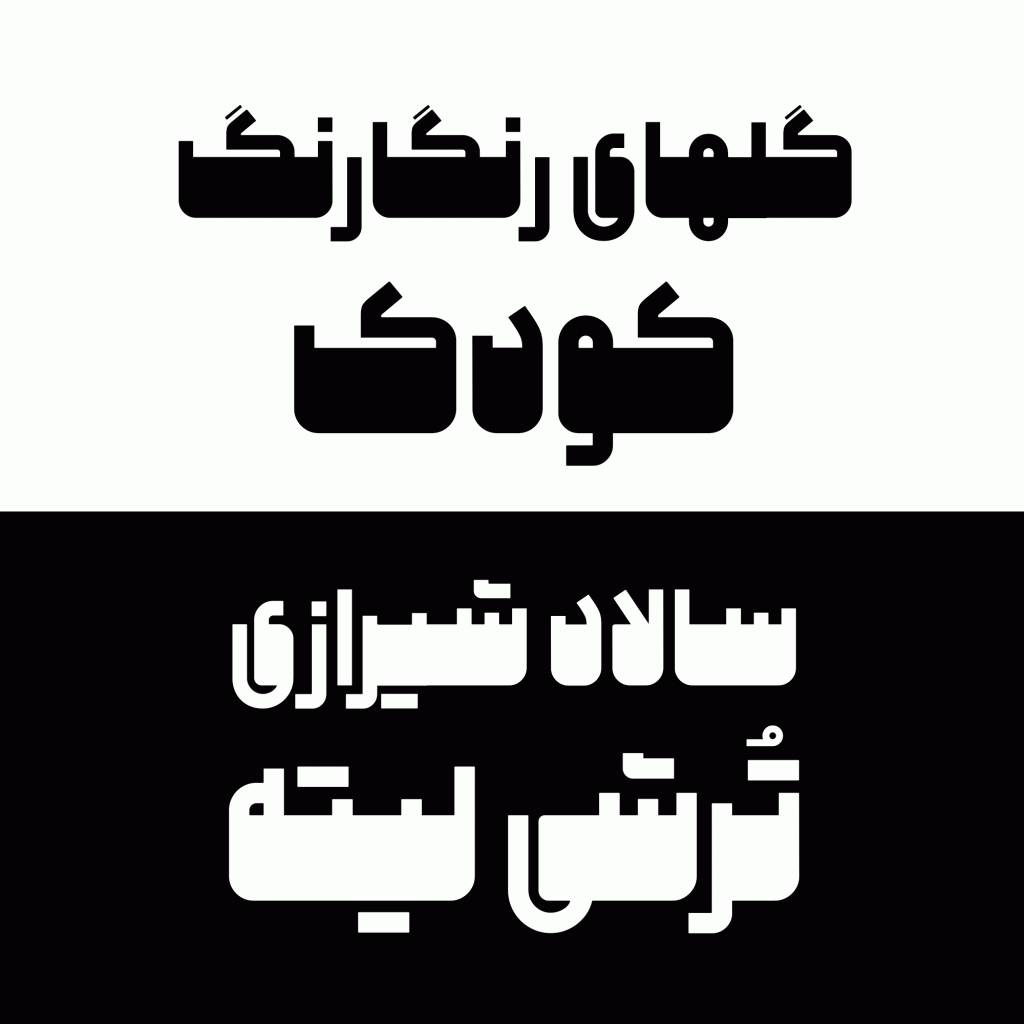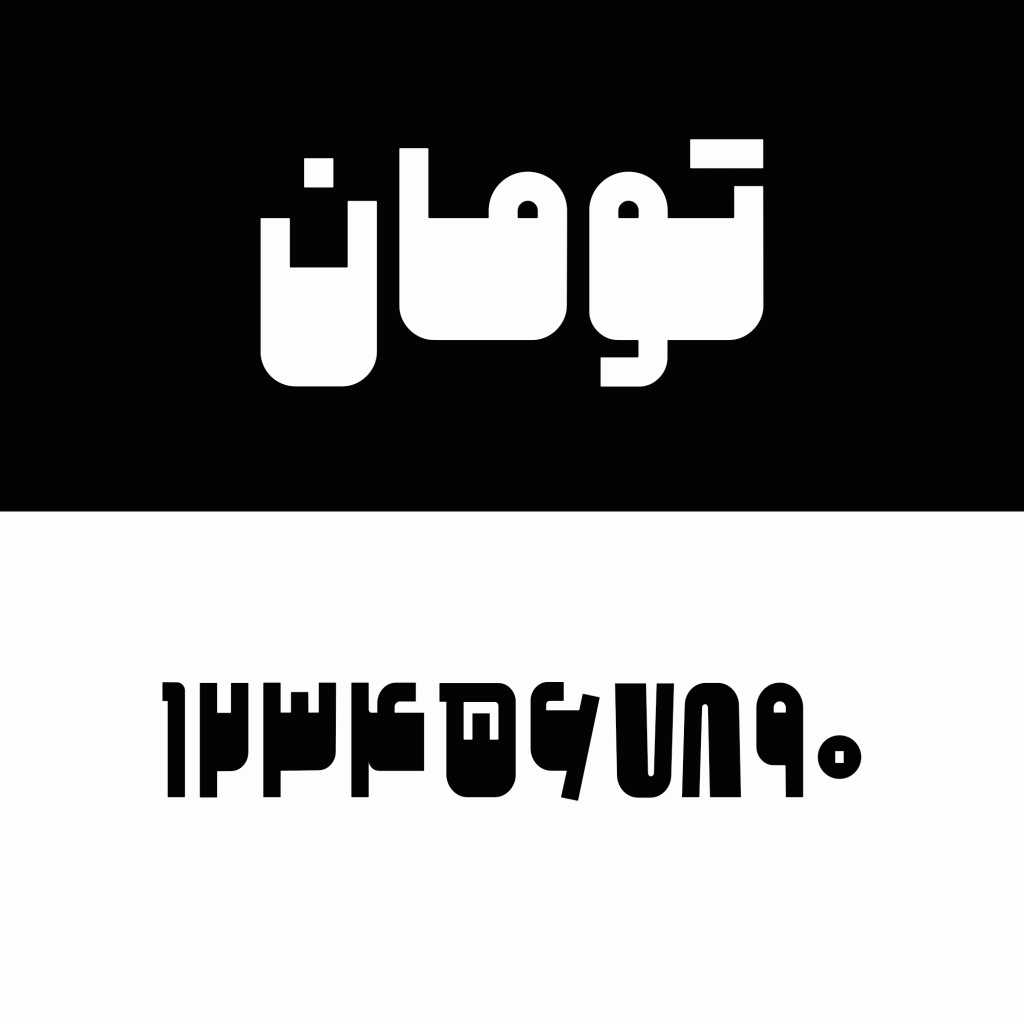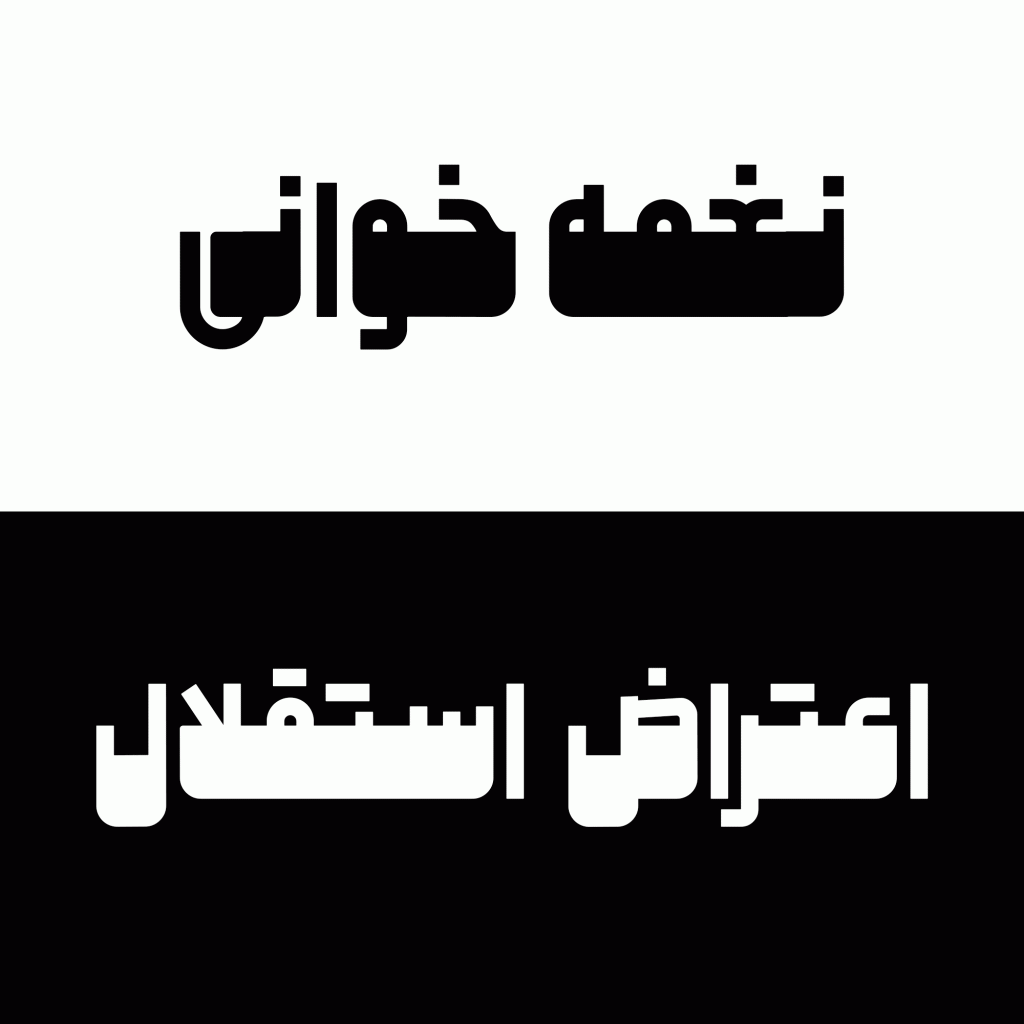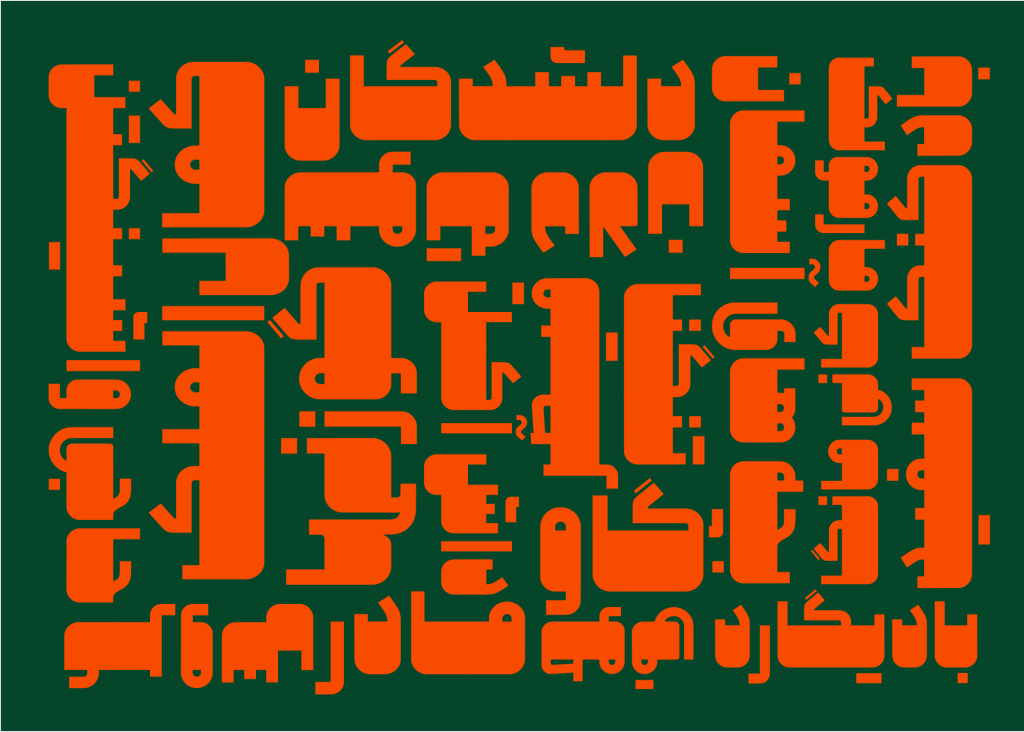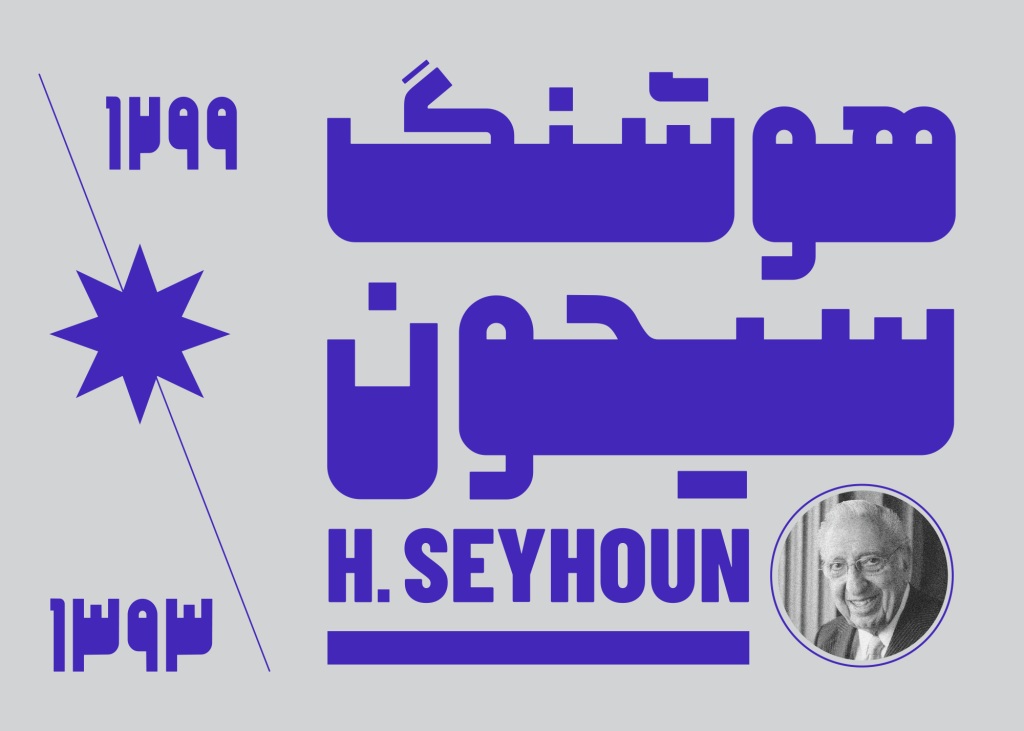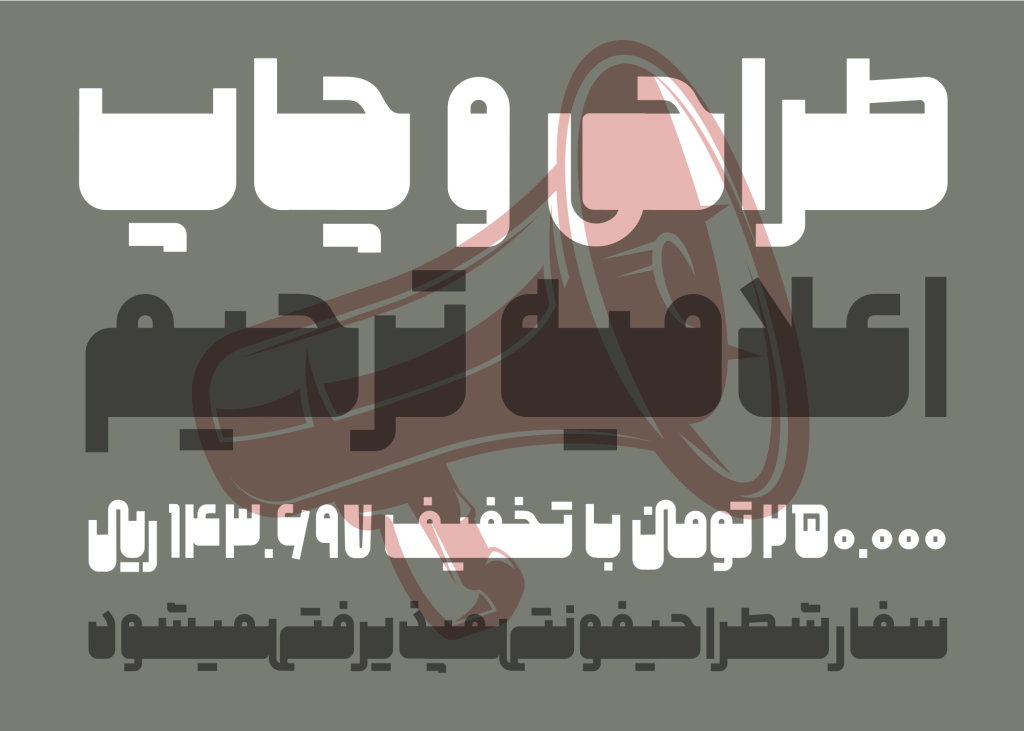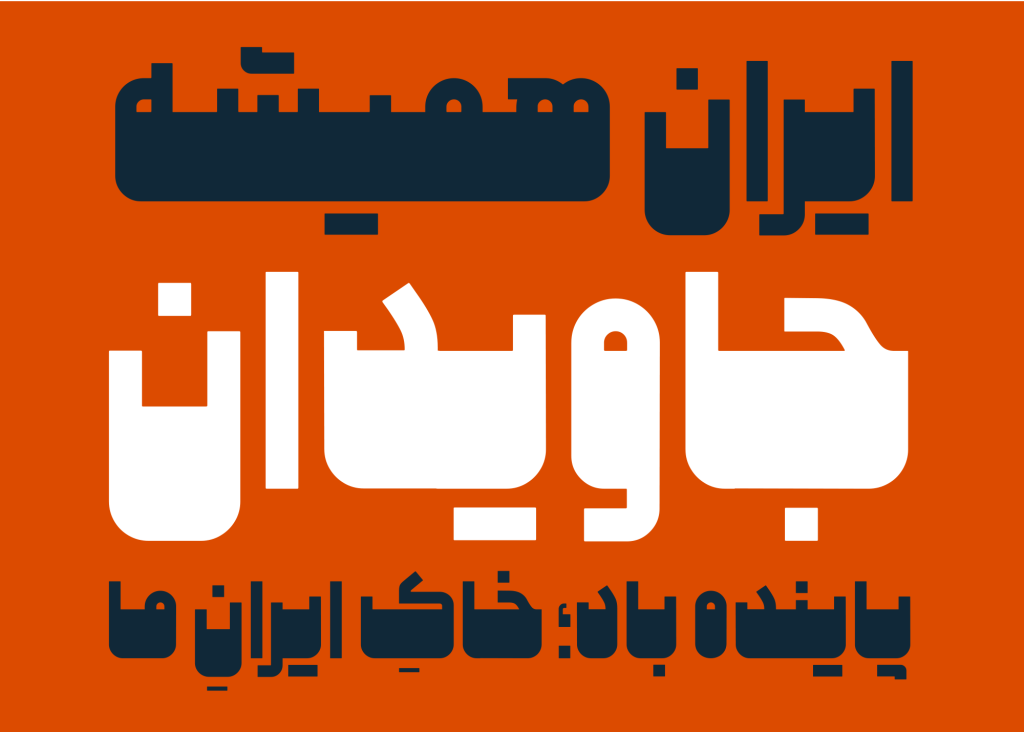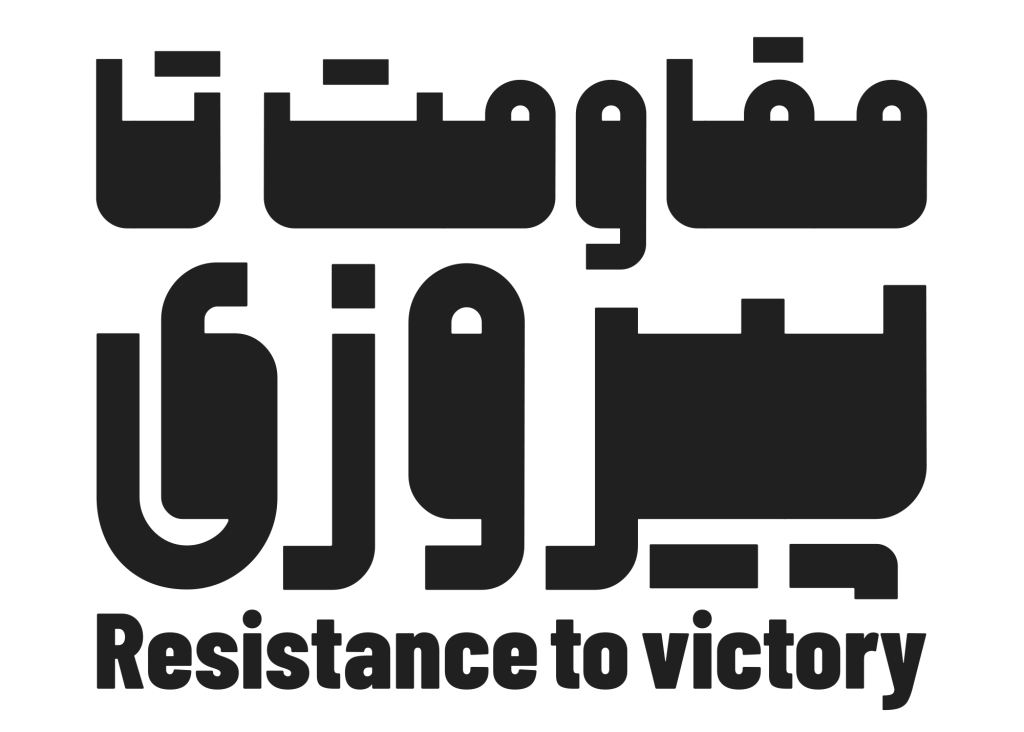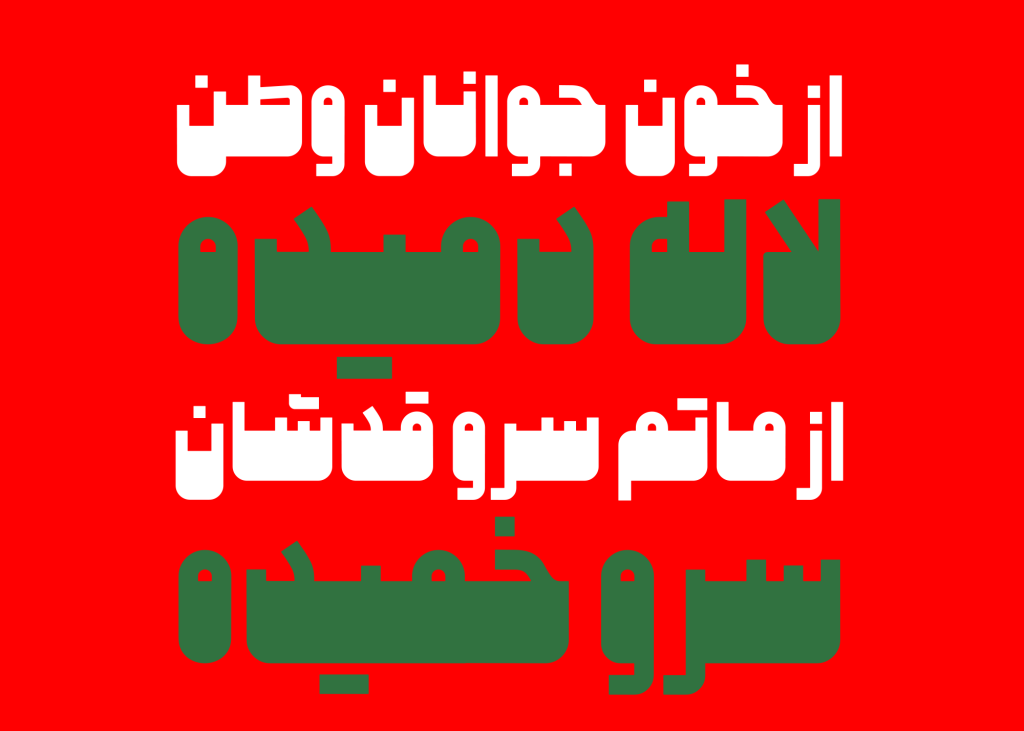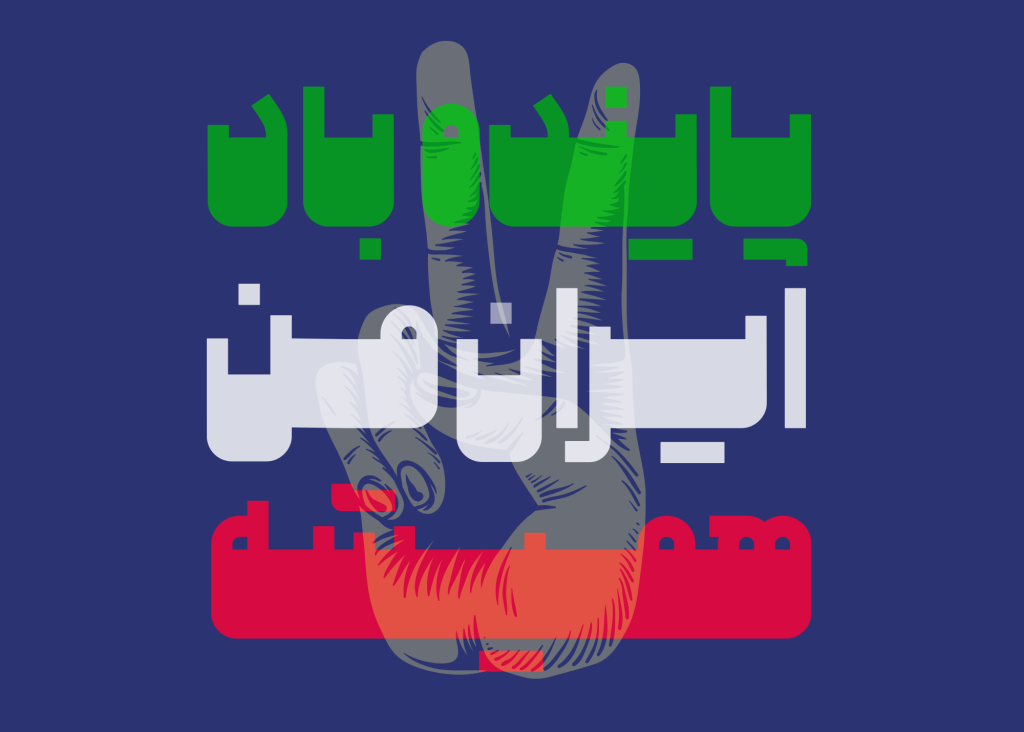
فونت ملی قلمی از خانواده هندسی که ویژگی بارز آن ضخامت اغراق آمیز در بدنه و ساقه های به نسبت باریک و نازک است که همین امر سبب ایجاد کنتراست زیاد در این تایپ فیس گردیده است.
فونت ملی
فونت ملی همانطور که در بالا اشاره کوتاهی به آن شد با دارا بودن ضخامتی نسبتا زیاد و اغراق آمیز از دسته فونت های حجیم و سنگین به شمار می رود. از طرفی دیگر نیز کاملا مشخص است که در ساقه ها به نسبت بدنه اصلی ضخامتی کم و باریک را شاهد هستیم. این تفاوت در ضخامت سبب کنتراستی اغراق آمیز شده است .
این قلم از دسته تایپ فیس های خانواده هندسی است و فرم های طراحی حروف آن متشکل از خطوط مستقیم و دایره می باشد البته با کمی دقت درمی یابیم طراحی آن از هندسه‌ای کنترل تبعیت می کند. و استفاده از منحنی ها در آن بسیار محدود و کم می باشد.
این قلم مناسب متون کوتاه و عناوین و تیتر ها می باشد حوزه کاربرد آن گستردگی مثال زدنی دارد می توان از این قلم در دنیای وب و دیجیتال تا صنعت نشر و چاپ بهره برداری کردبه طور ویژه می توان با استفاده از نرم افزار های طراحی نظیر ایلسترتور ، فتوشاپ و حتی اینشات برای طراحی کاور، جلد کتاب‌، پوستر و حتی بیلبورد ها و … از این قلم بهره لازم را برد.
تایپوگرافی و طراحی به وسیله این قلم سهل و آسان است. فشرده گی و منظم بودن باکس های حروف به گونه ای است که به آسانی همنشین تصویر و قاب شما می‌شوند.
از طرفی تایپ فیس ملی برای موضوعات و محتوا های حماسی، ملی، نوستالژی انتخابی بسار مناسب است. این قلم دارای شخصیتی جدی و جسور و با صلابت است که با دارا بودن جذابیت و ویژگی نمایشی نگاه مخاطبین را به خود جلب می کند
پشتیبانی قلم ملی از حروف و ترکیبات جایگزین
این تایپ فیس همچنین با پشتیبانی از حروف و ترکیبات جایگزین به شما علاقه مندان و طراحان امکان خلق تنوع و پویایی بیشتر را می دهد و دست شما عزیزان را جهت ایجاد تازگی و دوری از رخوت باز تر می نماید. در صفحه راهنمای این محصولنحوه فعالسازی این ترکیبات توضیح داده شده است.